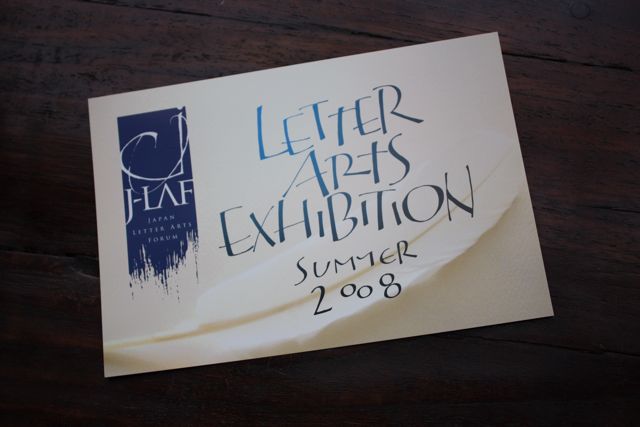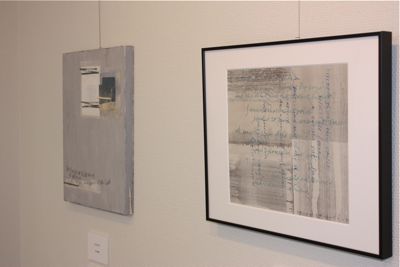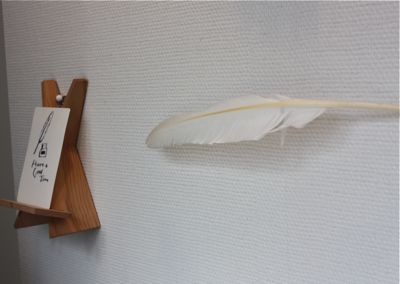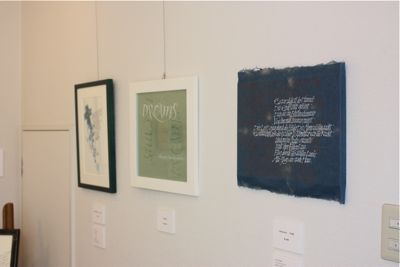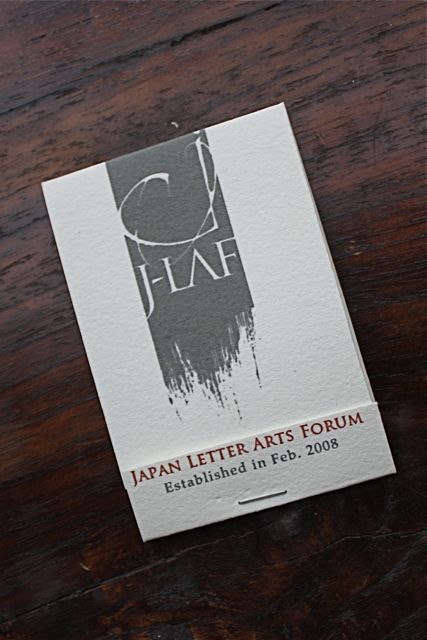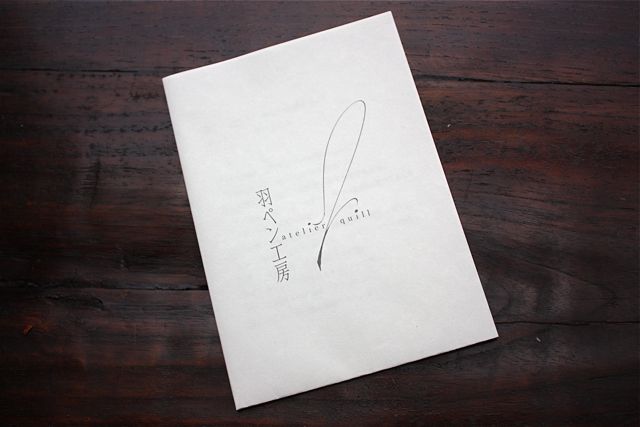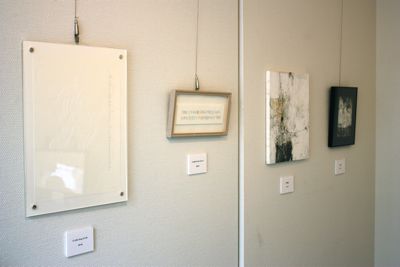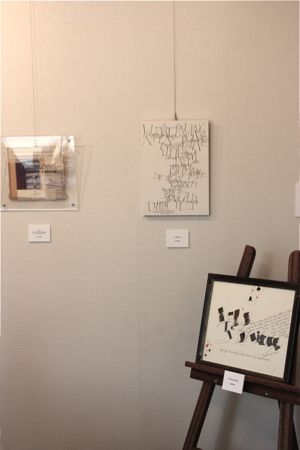
Letter Arts Exhibition Summer 2008
昨日から羽ペン工房でLetter Arts Exhinition Summer 2008が開催されています。
2008年夏〜2009年春の一年間で4回、J-LAF主催で作品展を開催します。第1回目となる今回は、J-LAFスタッフによる作品を展示しています。(今後この作品展はどなたでも参加出来ます。第2回目は9月末〜10月中旬を予定しています)作品は示し合わせた訳ではないのに、色がなんとなく揃っていて、とても良い空間です。文字が主体の作品、コラージュ作品、パネル張り、板にそのまま書いたもの、和紙を使ったもの、それぞれ素敵な作品ばかりです。
この作品展を主催しているジャパン・レターアーツ・フォーラム(J-LAF)は、カリグラフィーを軸とした日本におけるレターアーツ(文字芸術)の芸術性向上、レターアーツを介した海外との文化交流を目指し、その支援と交流を押し進めていく非営利団体として2008年2月に設立されました。
現在日本にあるカリグラフィーを含むレターアーツが、芸術の一翼を担うものとして広く認知されていくことを目的とし、アート活動の支援やアーティスト同士の交流を深めていきます。
J-LAFや羽根ペン工房のロゴもパンフも素敵ですよ〜!